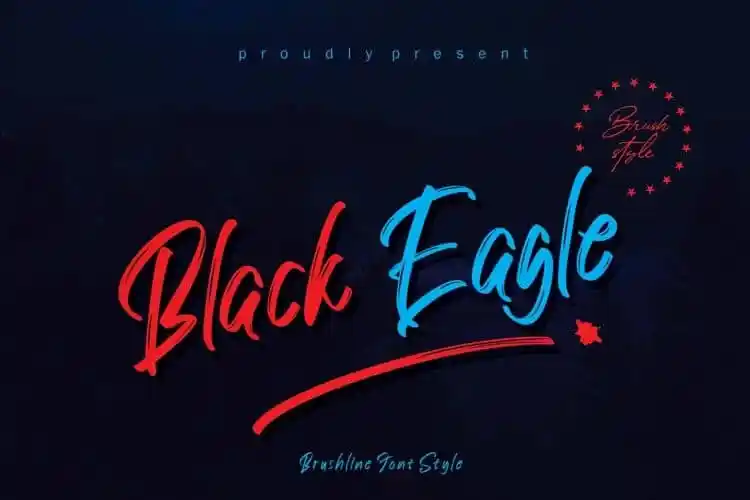
Black Eagle Brush Font – Download Grátis
Introduzimos a Black Eagle Brush Font – uma fonte fresca e única feita à mão pelo designer creativework69. Com seu estilo elegante e fluído, esta tipografia é perfeita para projetos pessoais e de logotipo, como cartões de coquetéis, cartazes, roupas, selos de marca, convites de casamento, layout de sites ou qualquer outro projeto que você possa imaginar. É especialmente atraente nas criações de identidade visual e design gráfico, onde você pode explorar seu estilo distintivo e eterno. Adotando o Black Eagle Brush Font é como adicionar um toque único ao seu próximo trabalho. Faça-se encantar pelo seu charme incomparável e aproveite para criar designs excepcionais!